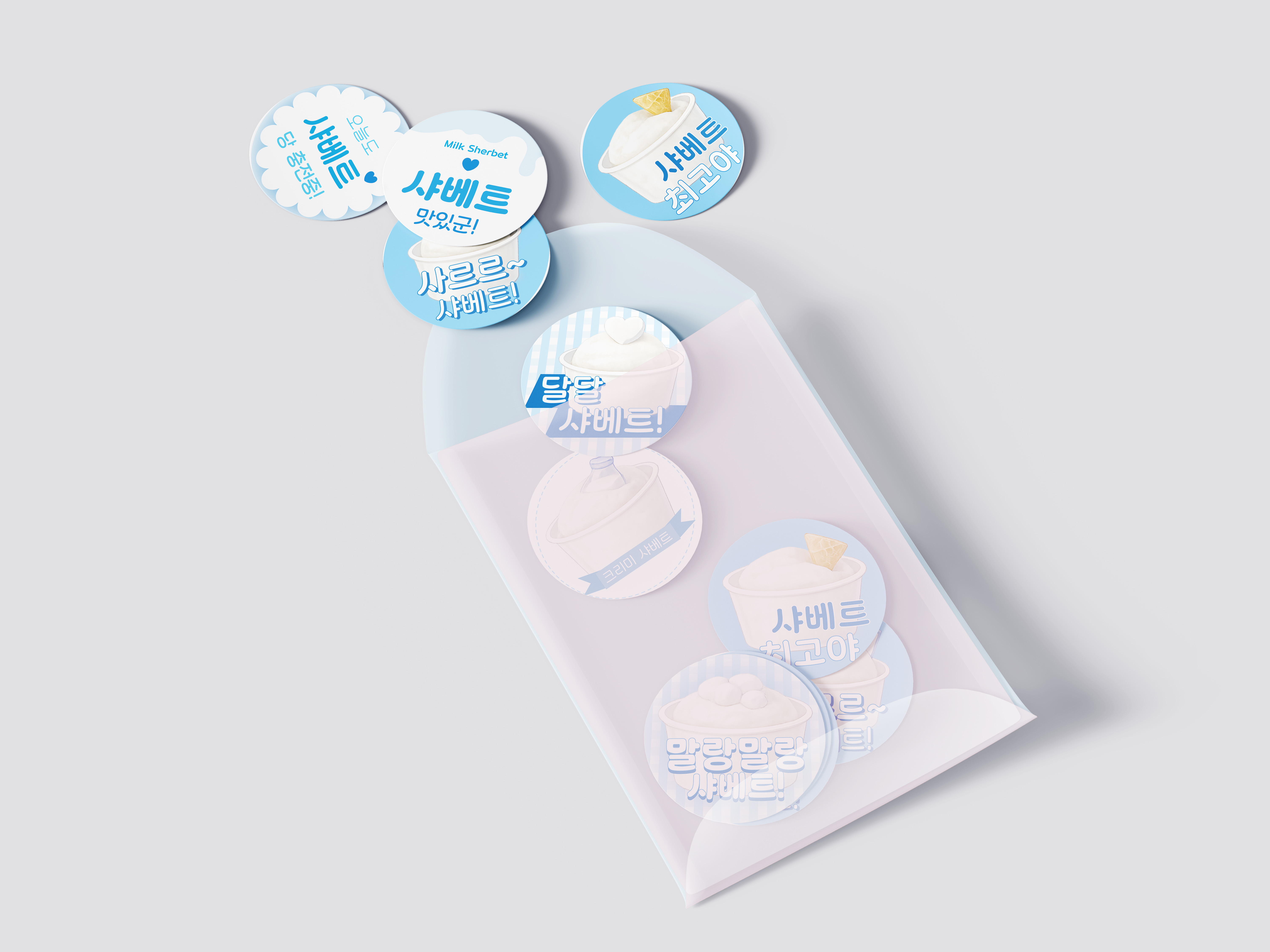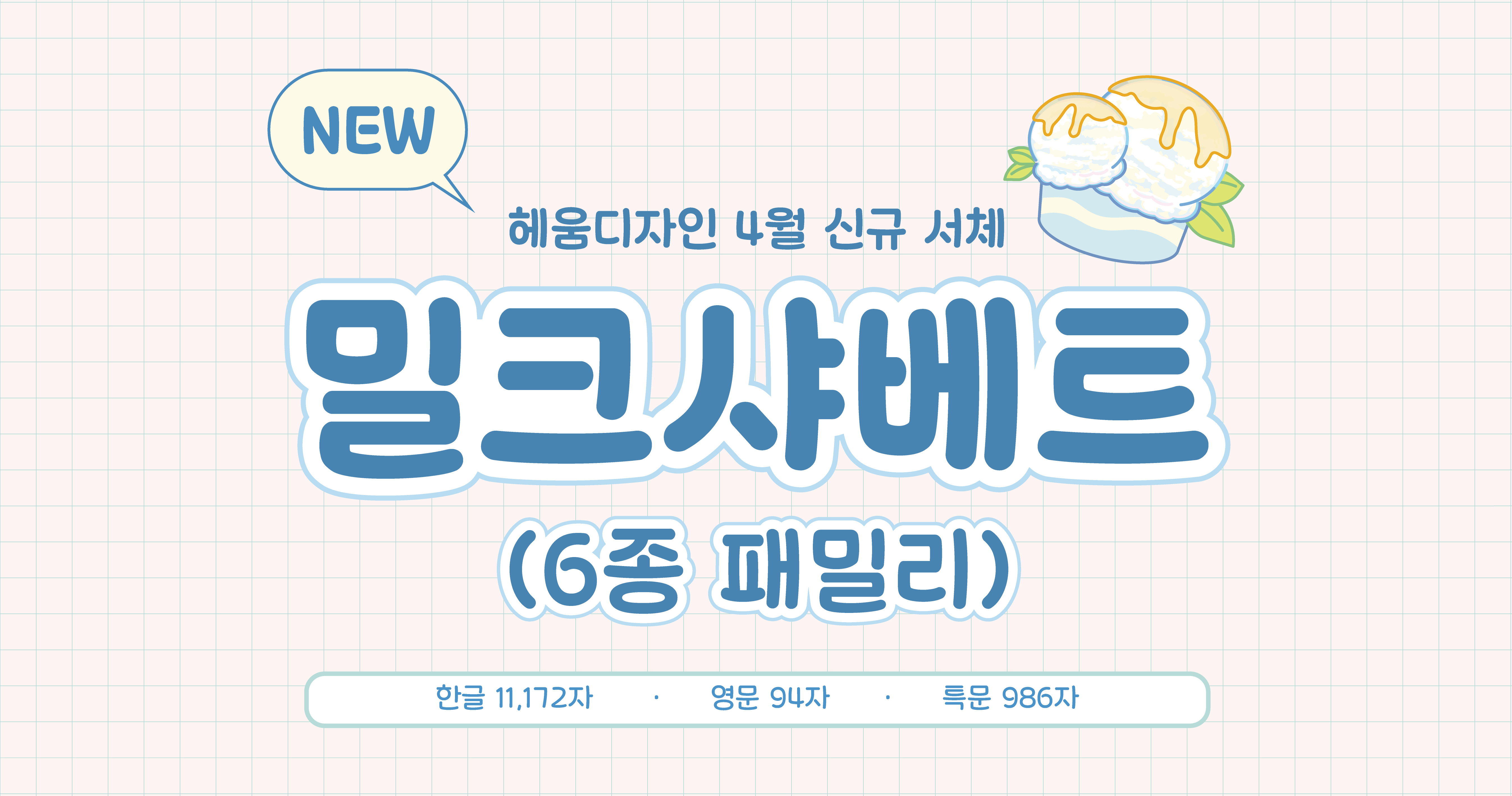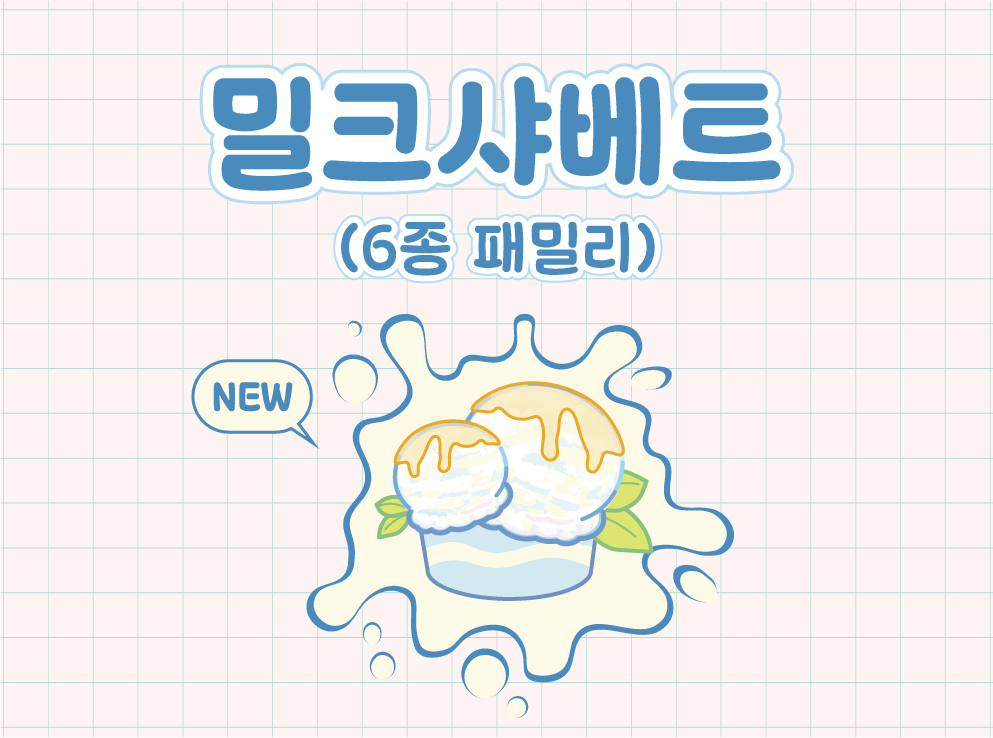
꽉 찬 모듈 구조를 기반으로 설계되었으며, 직선 대신 곡선 중심의 획 구성을 통해 전체적으로 부드럽고 유연한 인상을 형성한 서체.
폰트 HU밀크샤베트 패밀리
굵기 6종
* Light
* Regular
* Medium
* Bold
* ExtraBold
* Black
구성 KS한글 11,172자